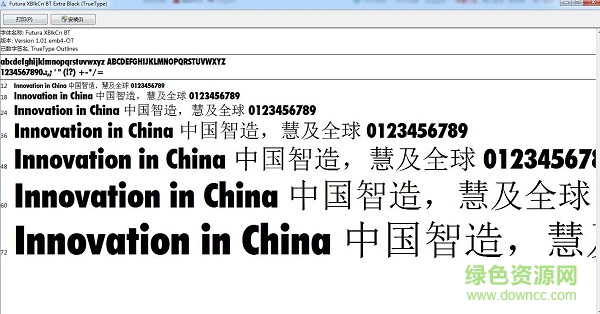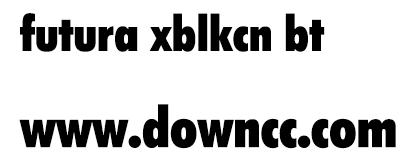
futura xblkcn bt
futura xblkcn bt字體是一款極富視覺沖擊力的英文粗體字體,字體細(xì)節(jié)十分豐富,棱角分明,邊緣光滑,筆畫舒展自然,可以用于促銷廣告、產(chǎn)品包裝等方面,感興趣的朋友快來下載吧!
futura xblkcn bt字體特點(diǎn)
風(fēng)格大方時(shí)尚、中和內(nèi)斂,每個(gè)字母都符合視覺和諧要求,可以滿足不同媒介的標(biāo)題和正文應(yīng)用,以及廣告標(biāo)語和包裝設(shè)計(jì)。